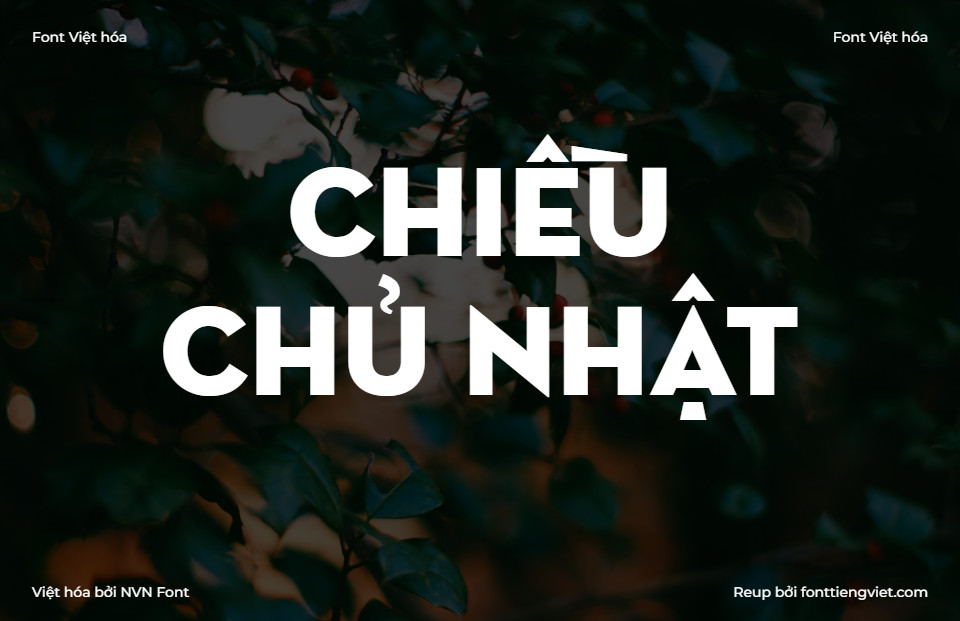
Font Việt hoá NVN Neutra Vintage
Giới thiệu về Font Việt hoá NVN Neutra Vintage
Trong thế giới thiết kế đồ họa hiện đại, việc tìm kiếm một bộ Font Miễn Phí mang đậm phong cách cổ điển nhưng vẫn giữ được sự tinh tế là điều vô cùng quan trọng. Font Việt hoá NVN Neutra Vintage chính là câu trả lời hoàn hảo cho những ai đang theo đuổi phong cách Art Deco sang trọng của những thập niên trước. Được lấy cảm hứng từ những đường nét kiến trúc hình học mạnh mẽ, bộ phông chữ này mang đến một diện mạo thanh lịch, gọn gàng và đầy tính nghệ thuật. Việc sử dụng Font Việt hoá NVN Neutra Vintage giúp các nhà thiết kế tại Việt Nam dễ dàng truyền tải thông điệp mà không lo ngại về lỗi hiển thị dấu tiếng Việt, vốn là trở ngại lớn đối với các bộ phông quốc tế nguyên bản. Đây là lựa chọn lý tưởng để tạo nên sự khác biệt cho các dự án sáng tạo từ học đường đến chuyên nghiệp.
Đặc điểm nổi bật của Font Việt hoá NVN Neutra Vintage
Phong cách thiết kế hình học tinh xảo
Đặc trưng lớn nhất của Font Việt hoá NVN Neutra Vintage nằm ở cấu trúc hình học chuẩn xác. Các chữ cái được tạo hình với tỉ lệ cân đối, khoảng cách hợp lý, tạo nên cảm giác thoáng đãng và dễ đọc. Sự kết hợp giữa các nét thẳng dứt khoát và những đường cong mềm mại giúp bộ font này thoát khỏi sự khô cứng, mang lại vẻ đẹp hoài cổ nhưng vẫn rất thời thượng. Khi ứng dụng vào các tiêu đề lớn, bộ chữ tỏa sáng với quyền năng thu hút thị giác mạnh mẽ, giúp nội dung trở nên nổi bật ngay từ cái nhìn đầu tiên.
Khả năng tương thích và tối ưu hóa tiếng Việt
Phiên bản Font Việt hoá NVN Neutra Vintage đã được tinh chỉnh kỹ lưỡng về hệ thống dấu thanh. Các dấu tiếng Việt được thiết kế đồng nhất với độ dày và góc nghiêng của chữ cái chính, đảm bảo tính thẩm mỹ cao nhất. Điều này cực kỳ hữu ích cho các bạn học sinh, sinh viên khi làm báo cáo, thuyết trình hoặc các thầy cô giáo muốn trang trí bảng tin nhà trường theo phong cách cổ điển. Sự chỉn chu trong từng ký tự giúp văn bản tiếng Việt trở nên chuyên nghiệp và sang trọng hơn bao giờ hết.
Ứng dụng thực tế của Font Việt hoá NVN Neutra Vintage
Thiết kế thương hiệu và quảng cáo
Với vẻ ngoài đẳng cấp, Font Việt hoá NVN Neutra Vintage thường xuyên xuất hiện trong các bộ nhận diện thương hiệu cao cấp như logo quán cà phê, nhà hàng hoặc các bìa tạp chí thời trang. Nó giúp gợi nhớ về một kỷ nguyên vàng son của nghệ thuật thiết kế, tạo dựng niềm tin và sự hoài niệm cho khách hàng. Ngoài ra, phông chữ này còn rất phù hợp để làm poster sự kiện hoặc các ấn phẩm truyền thông đòi hỏi sự trang trọng và lịch thiệp.
Sáng tạo nội dung trên mạng xã hội
Nếu bạn là một người sáng tạo nội dung, việc sử dụng Font Việt hoá NVN Neutra Vintage cho các bức ảnh trích dẫn (quotes) hoặc ảnh bìa video sẽ giúp kênh của bạn có gu hơn hẳn. Sự tối giản nhưng đầy cá tính của font chữ này giúp thông điệp của bạn dễ dàng đi sâu vào tâm trí người xem, tạo nên một phong cách cá nhân riêng biệt và không lẫn lộn với đám đông.
Kết luận về bộ phông chữ ấn tượng này
Có thể khẳng định rằng, Font Việt hoá NVN Neutra Vintage là một công tài liệu quý giá cho cộng đồng thiết kế Việt. Sự kết hợp giữa giá trị lịch sử của phong cách Neutra và sự tiện dụng của bản Việt hóa đã tạo nên một bộ phông chữ đa năng, đáp ứng mọi nhu cầu từ học tập đến công việc thực tế. Nếu bạn đang tìm kiếm sự độc đáo cho tác phẩm của mình, đừng ngần ngại truy cập Font Miễn Phí, Font Việt Hóa, Font Việt hoá NVN Neutra Vintage để tải về và trải nghiệm. Hãy để những đường nét tinh tế của bộ font này nâng tầm giá trị cho mọi ý tưởng sáng tạo của bạn ngay hôm nay.